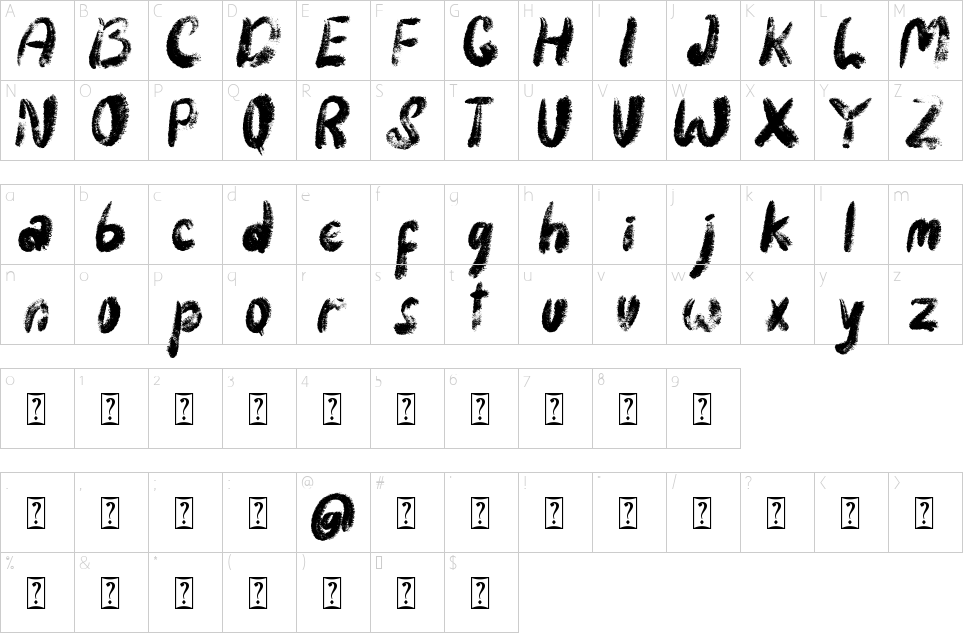
A fonte Zombie Predator é uma escolha única para qualquer designer que busca um ar pesado e distópico para seus projetos. Desenhada por Yoga Letter, esta fonte tem se destacado como uma opção ideal para criar elementos de jogo ou materiais visuais com temas sobrenaturais ou futuristas. Com uma abordagem brutalmente minimalista, Zombie Predator oferece linhas agressivas e estilos de letra desajeitados que certamente irão chamar a atenção em qualquer projeto. Através do download gratuito disponível para os sistemas operacionais Windows e Mac, esta font se torna um recurso versátil para designers gráficos profissionais e iniciantes. Seja criando grafismos de mídia social, adesivos ou elementos para jogos digitais, a Zombie Predator se encaixa perfeitamente em muitas necessidades visuais. Com 1,545 downloads confirmados, é evidente que os designers encontraram em Zombie Predator uma fonte forte e divertida. Se você está procurando por uma opção única para seu próximo projeto, certamente a Zombie Predator será um ótimo escolha.